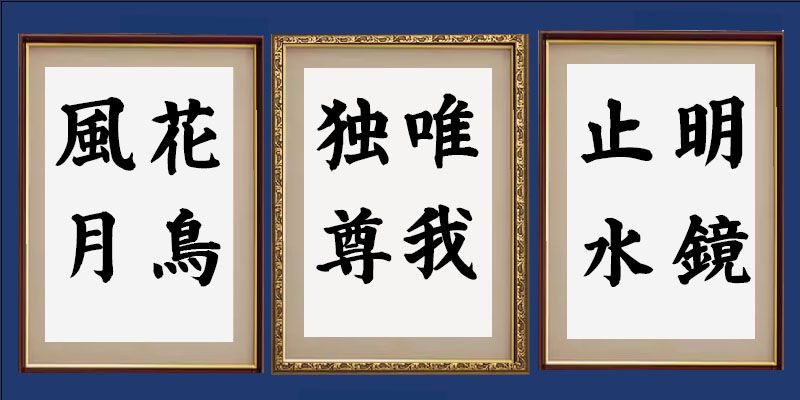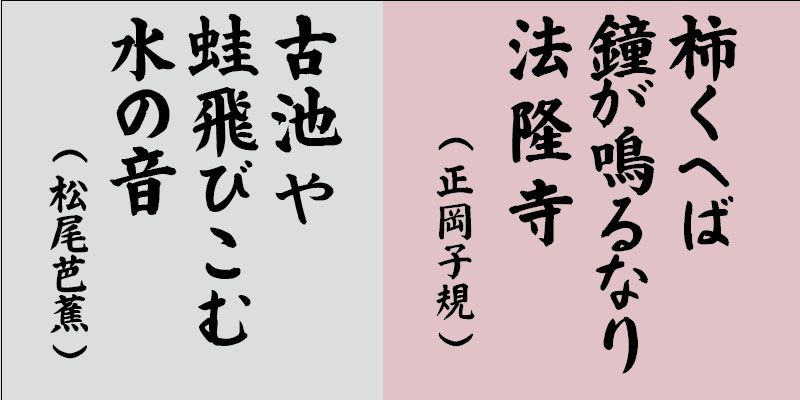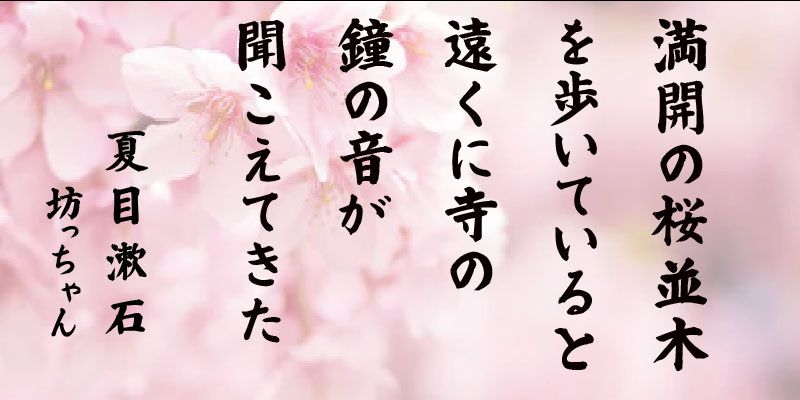
力強くダイナミックなストローク構成が特徴のこの書体は、看板やポスター、サムネイルのデザインに効果的です。
この書体ファミリーの各フォントに含まれる英数字、ひらがな、カタカナは、それぞれ独自の文字幅を持つプロポーショナル字形としてデザインされています。
書道家の中本白洲は、60 年以上の書道経験を活かし、美しく巧みに手書きされた字形の筆文字フォントを創作しました。プロの書家として活動し、様々なクライアントのニーズに応えるカスタムサービスを提供しています。中本のデザインを使用することで、伝統的な書道の芸術にさらに親しむことができます。